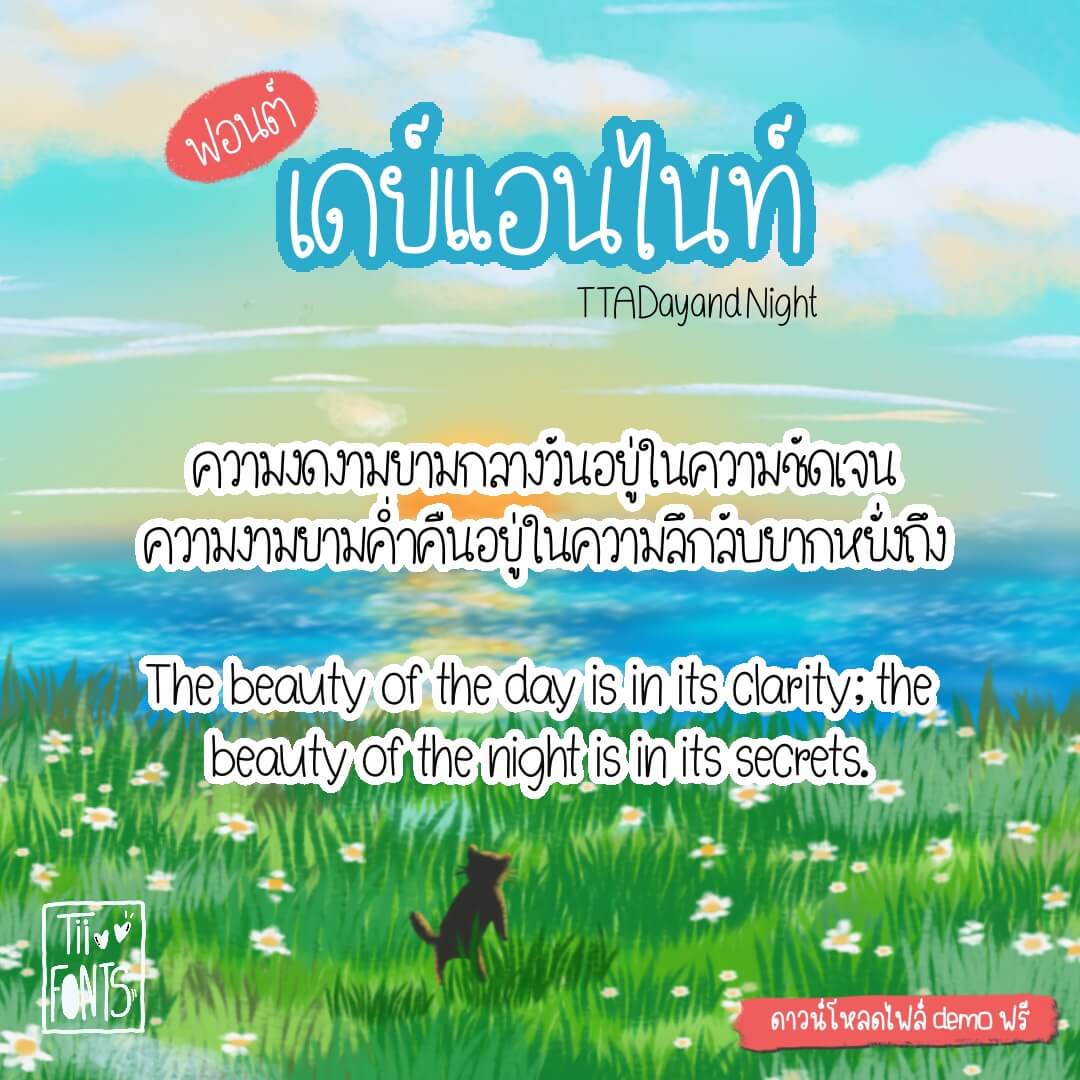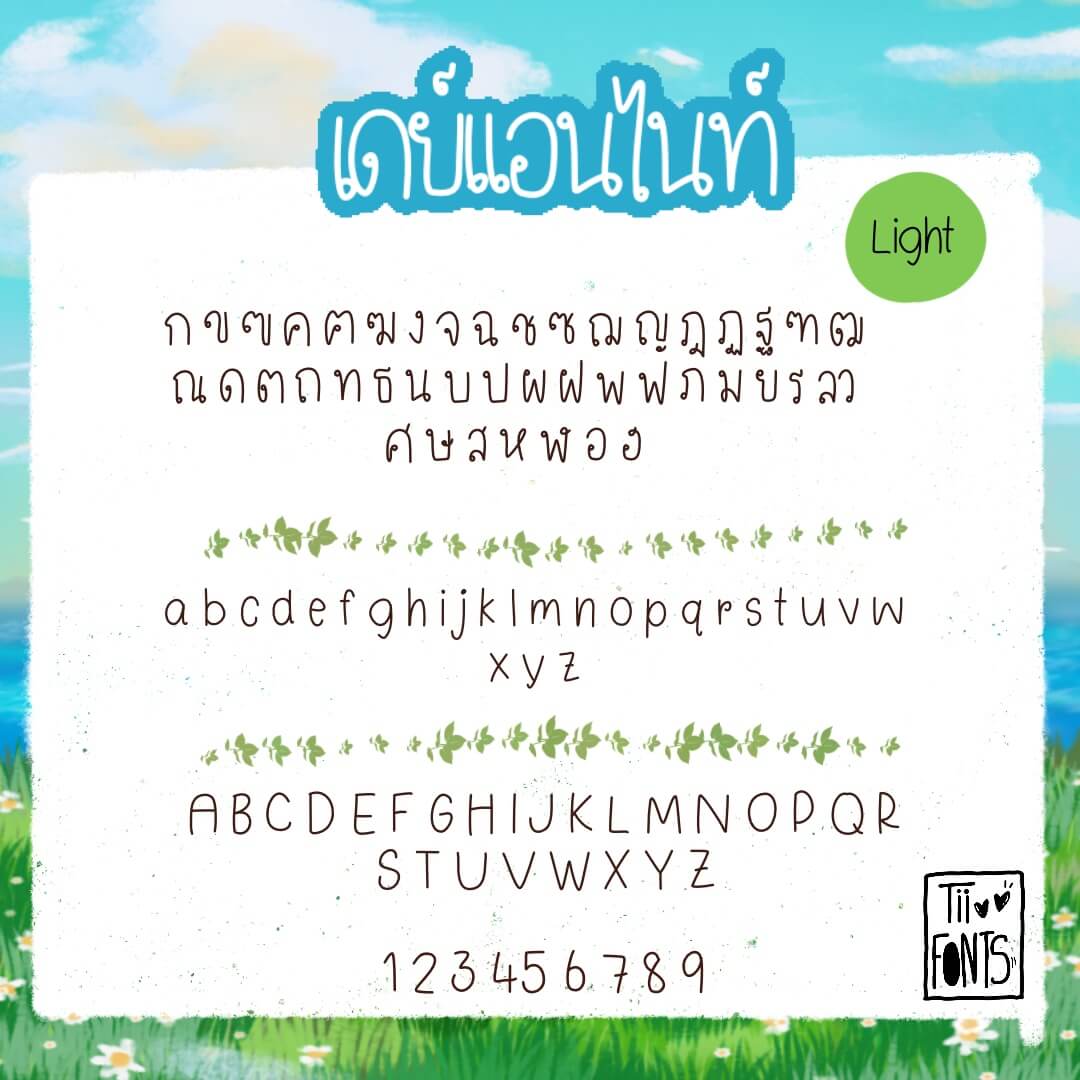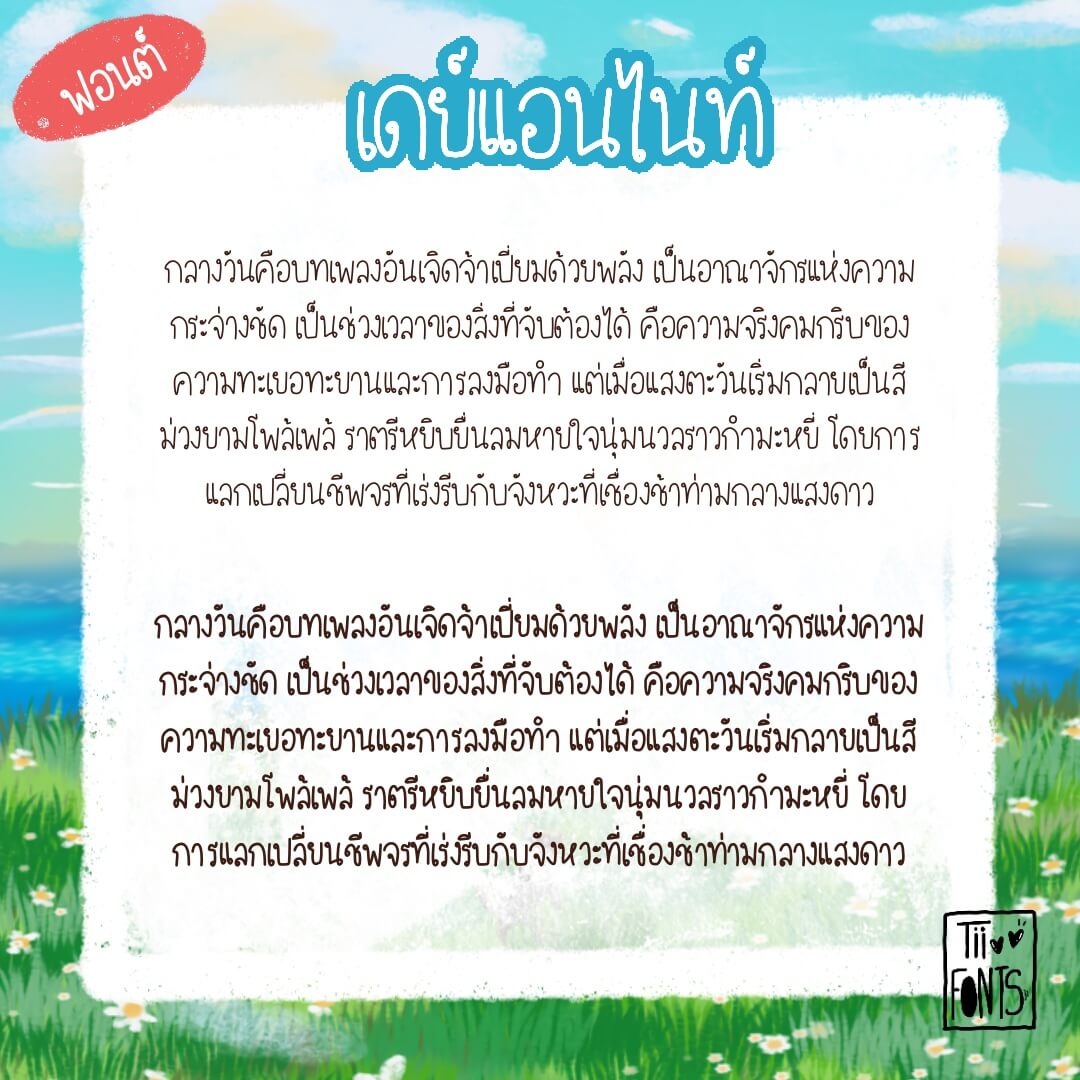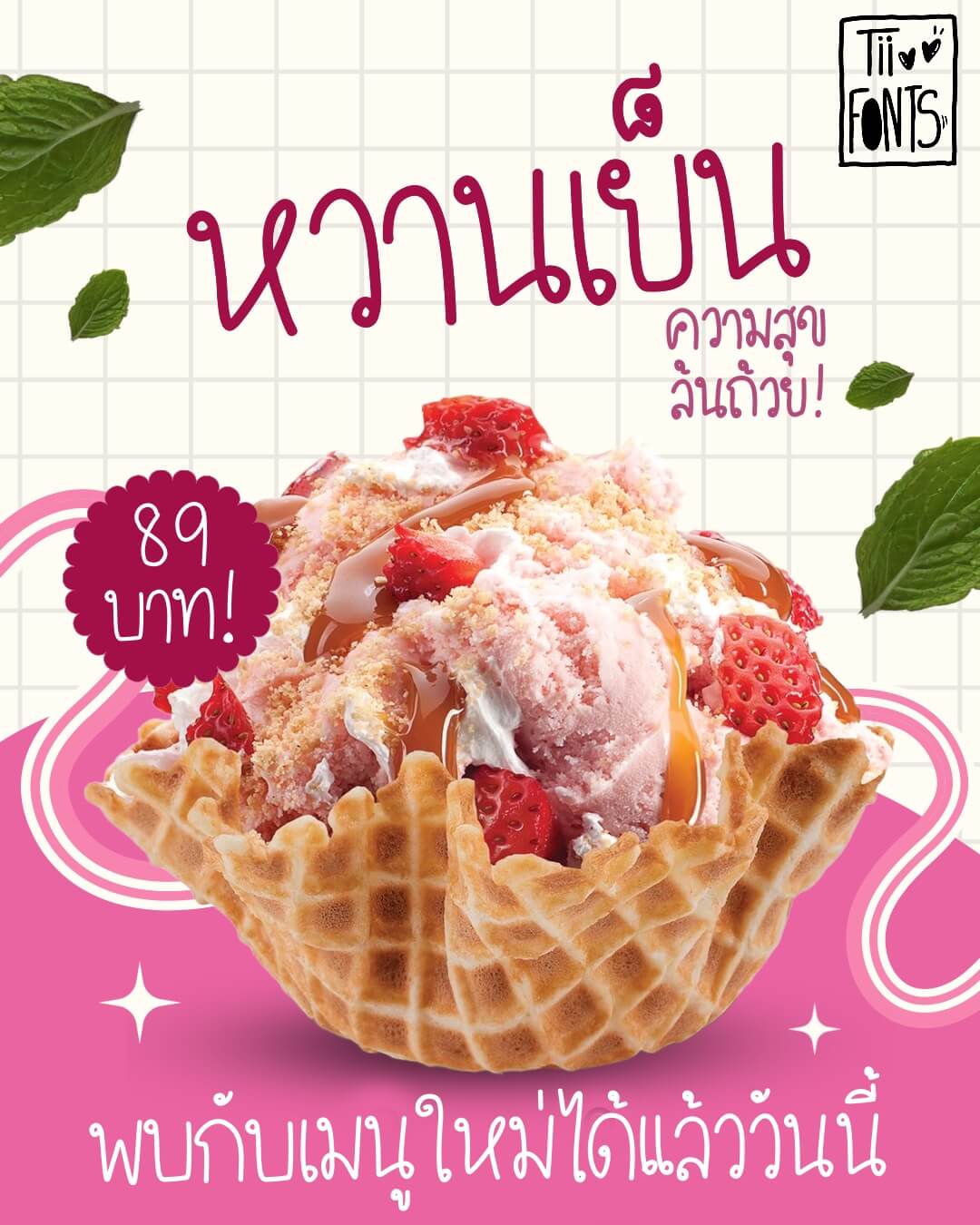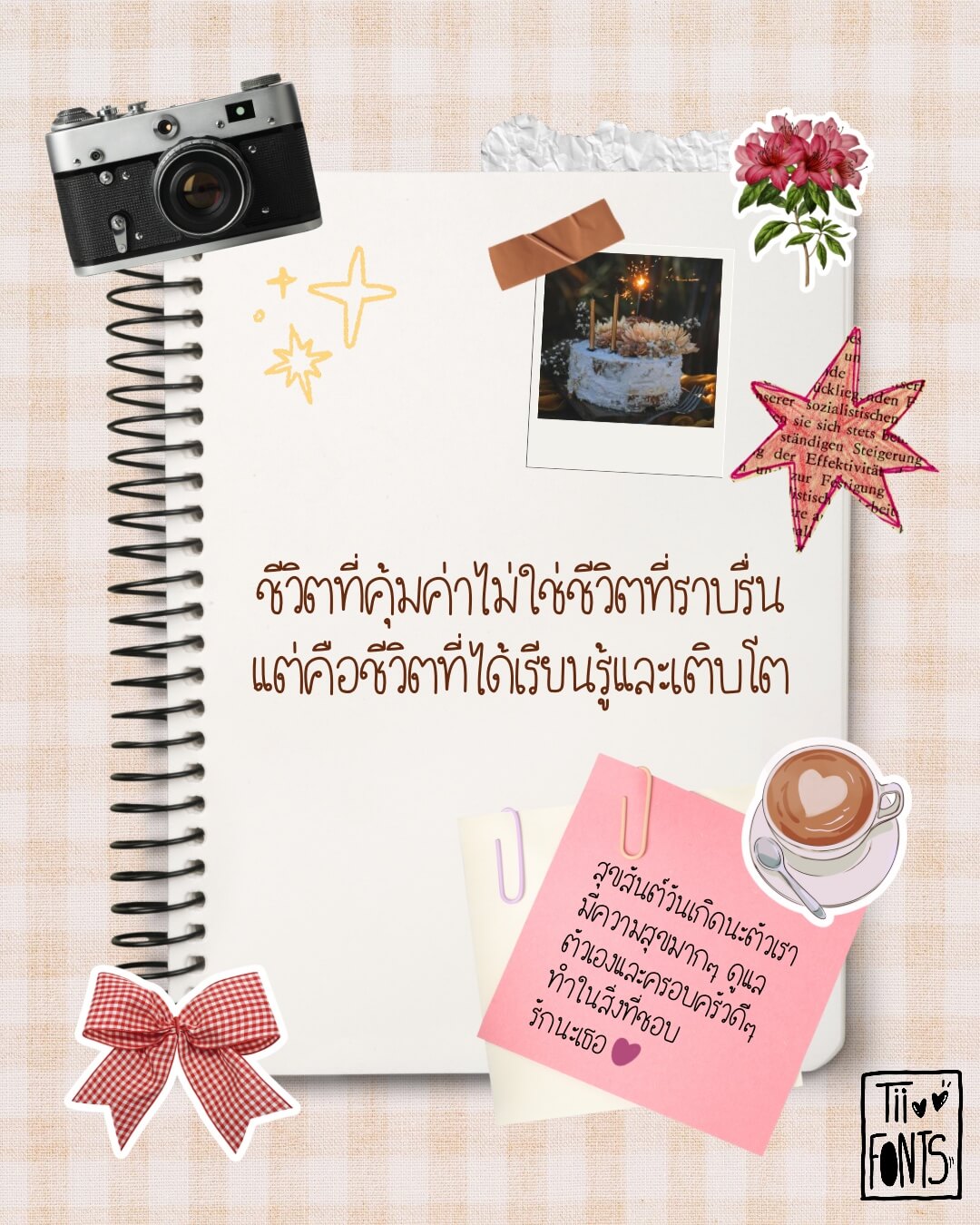
เดย์แอนไนท์ (TTA Day and Night)
ฟอนต์ลายมือสุดคิ้วท์ที่ใช้ได้ดีทั้งกลางวันและกลางคืน จะจดโน้ต ทำสรุป หรือแต่งรูปก็น่ารักไปหมด
​จัดเต็ม 2 น้ำหนัก:
Light: เส้นบางเบา ดูสะอาดตา เหมาะกับงานสายมินิมัล
Regular: เส้นมาตรฐาน อ่านง่าย ชัดเจน